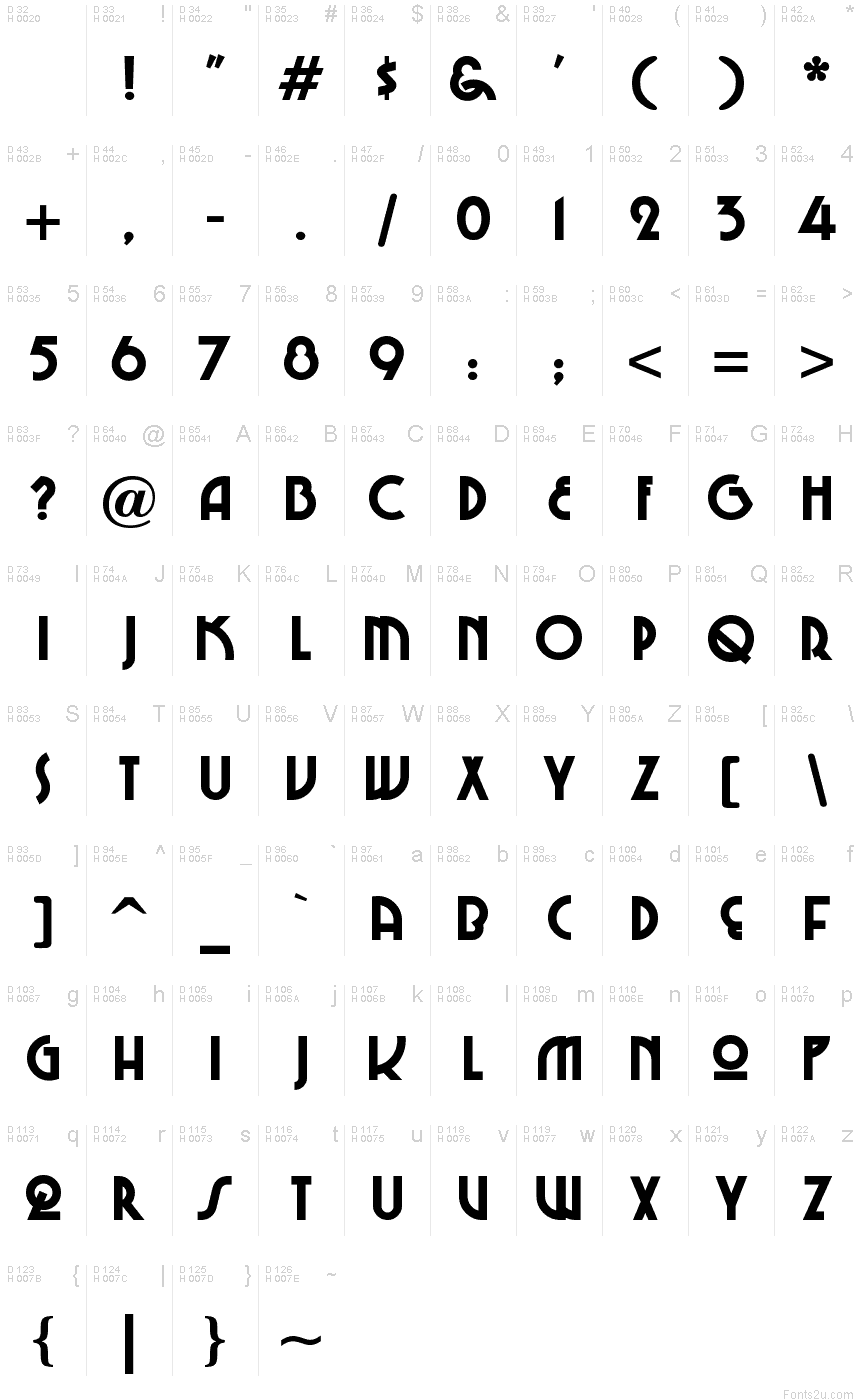
Chi-Town autorstwa Nicka Curtisa to darmowy krój pisma typu display w stylu retro. Wysokie, blokowe litery i masywna geometria przywodzą na myśl wyraziste szyldy, z charakterystycznym, okrągłym „O” osadzonym na solidnej poprzeczce niczym reflektor na scenie. Grube kreski dają gęsty, głęboki czarny druk, co nadaje nagłówkom silną, niemal namacalną obecność – łatwo czytelną z daleka i pełną charakteru z bliska.
Dzięki Chi-Town Twoje projekty natychmiast zyskują energię wielkiego miasta z połowy wieku. Świetnie sprawdza się na plakatach, ulotkach, okładkach płyt, logotypach, opakowaniach i wyrazistych nagłówkach stron internetowych. Równomierne odstępy i solidna budowa znaków wyglądają znakomicie w dużych rozmiarach, gdzie nietypowe kształty mogą naprawdę wybrzmieć. Ten darmowy font doskonale łączy się z czystym, lekkim krojem bezszeryfowym w tekście głównym – pozwól Chi-Town zająć się krzykliwymi nagłówkami, podczas gdy reszta treści pozostanie spokojna i przejrzysta.